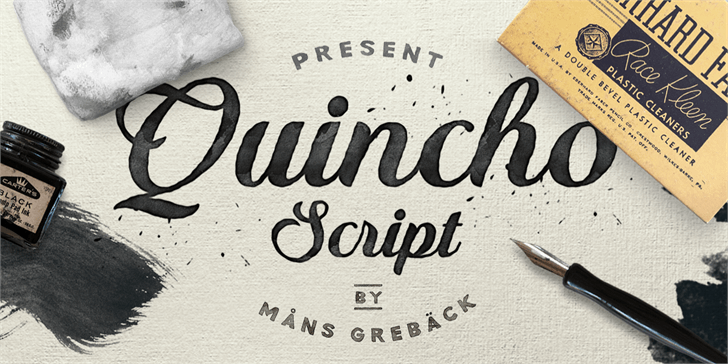
A Fonte Quincho Script é uma criação única do designer Måns Grebäck que se destaca no universo das fontes tipográficas. Desenvolvida em 2016, essa elegante escolha de letra é perfeita para designers e artesãos buscando adicionar um toque distintivo a seus trabalhos criativos. Com linhas delicadas e arredondadas que remetem à calligrafia, Quincho Script oferece uma experiência visual deslumbrante em qualquer projeto personalizado ou aplicado com cuidado. Com sua tipografia sem seriedade, Quincho Script enriquece os projetos de design gráfico, especialmente quando se trata de elementos mais delicados e arredondados. Seu uso é ideal para criar mensagens agradáveis e confortáveis em cartões de apresentação, identidades digitais, ou até mesmo designs gráficos que requerem uma aparência cuidadosamente elaborada. Como fonte Personal Use criada por Måns Grebäck, Quincho Script se destaca na categoria de calligraphy fonts, trazendo beleza e elegância aos seus projetos. É uma excelente escolha para quem busca adicionar um toque personalizado à sua obra de arte, sem comprometer a qualidade ou o estilismo de seu design. Com características únicas que não podem ser encontradas em outras fontes de calligraphy, Quincho Script oferece uma opção exclusiva para aqueles buscando personalizar suas criações com um toque diferenciado e elegante.